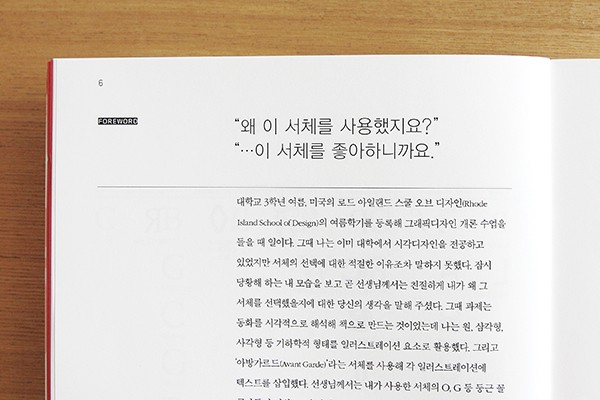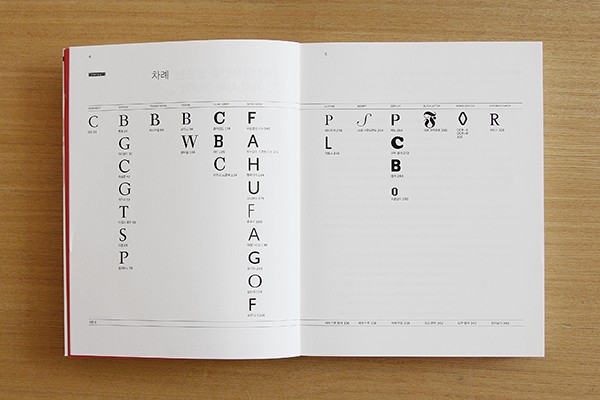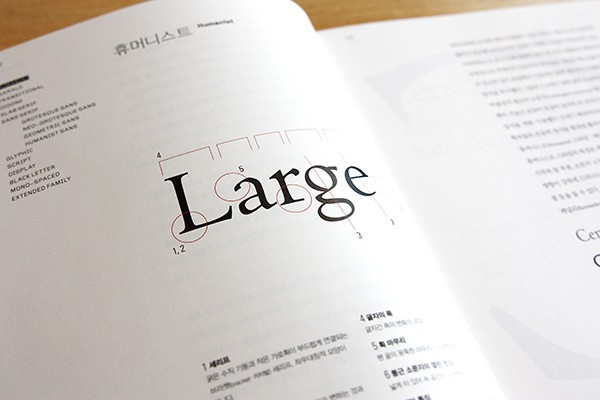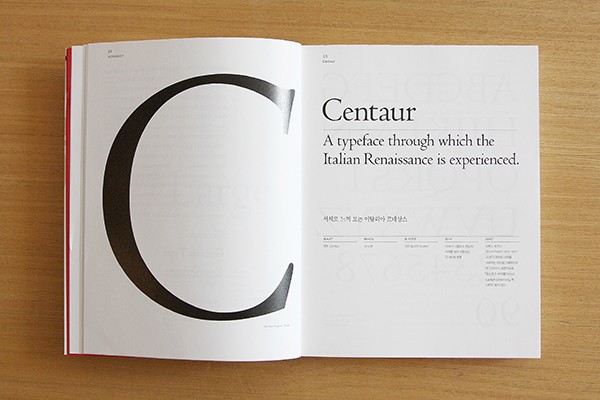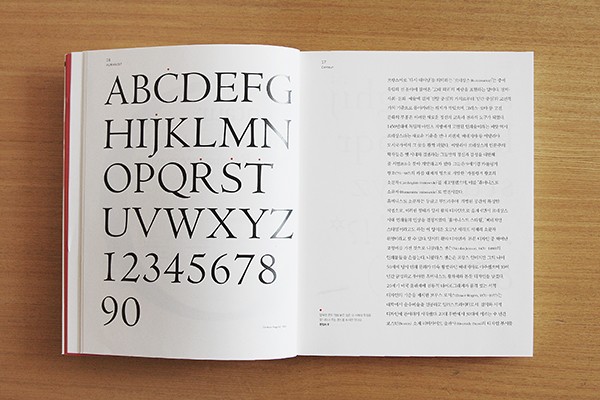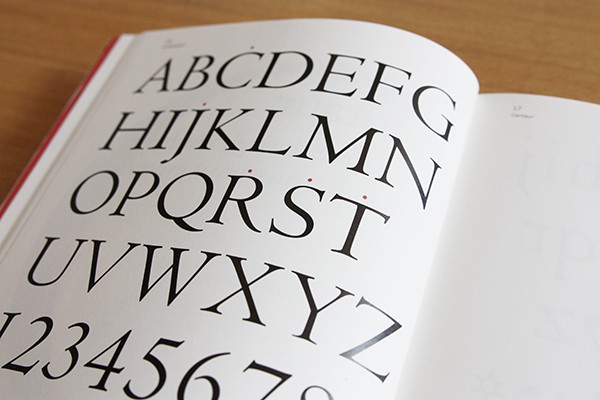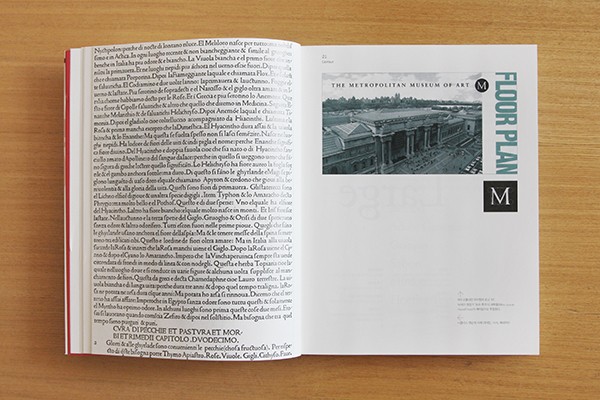
<좋은 디자인을 만드는 33가지 서체 이야기> : 기능과 아름다움이 검증된 서체 모음집
서체를 둘러싼 다양한 정보와 형태에 대한 이해는 모두 디자이너의 시각적 선택의 근거이자 문제 해결의 열쇠가 된다. 디자인을 하면서 콘셉트에 따른 이미지와 서체에 대한 고민을 해야 할 때가 많다. 전달에서 이미지에 따른 시각적인 부분도 크지만, 서체에 따라 디자인 성격이 달라지는 것을 볼 수 있다.
좋은 디자인을 만드는 33가지 서체 이야기
학생 때 이후로 다시 한 번 펼쳐 본 <좋은 디자인을 만드는 33가지 서체 이야기>는 디자인을 전공하는 학생이라면 분야를 가리지 않고 추천하고 싶다. ‘서체’는 디자이너가 갖추어야 할 기본 소양이라고 할 수 있는데, 흩어져있는 서체에 대한 정보를 타이포그래피 역사에서 기능과 아름다움이 검증된 서체들로 잘 엮어둔 고마운 책이다.
1. 센토 – 서체로 느껴 보는 이탈리아 르네상스
2. 벰보 – 황금의 파트너십이 창조한 서구 로만 서체의 원형
3. 게라몬드 – 우아하고 품격 있는 세리프 서체의 원형
4. 캐슬론 – 프랑스에는 게라몬드가, 영국에는 캐슬론이
5. 가우디 – 미국에서 탄생한 특별한 로만 서체
6. 타임스 로만 – 신문을 위해 탄생한 ‘전천후’ 서체
7. 사봉 – 타이포그래피의 거장 얀 치홀트가 남긴 선물
8. 팔라티노 – 펜글씨의 생동감이 특징인 로만 서체
9. 베스커빌 – 18세기에 등장한 모던한 인물의 모던한 서체
10. 보도니 – 이탈리아가 선사한 ‘서체의 꽃’
11. 발바움 – 가장 독창적인 독일의 낭만주의 서체
12. 클라렌든 – 산업혁명 시대에 나타난 본문용 서체
13. 시티 – IBM 로고의 모태가 된 서체
14. 센추리 스쿨북 – 두 세대에 걸친 재능과 땀이 만들어 낸 서체
15. 프랭클린 고딕 – 미국의 모더니즘을 보전하는 서체
16. 악치덴츠 그로테스크 – 신 타이포그래피의 전통을 잇는 서체
17. 헬베티카 – 20세기 공식 서체
18. 유니버스 – 타이포그래픽 컬러 팔레트
19. 퓨추라 – 바우하우스의 정신을 실현한 서체
20. 아방가르드 – 미국 잡지 디자인의 황금기에 태어난 서체
21. 길 산스 – 가장 영국적인 서체
22. 옵티마 – 세리프와 산세리프의 최적의 배합
23. 프루티커 – 파리 공항의 사인을 위해 만든 서체
24. 퍼피추아 – 조각가 에릭 길의 조각한 듯한 서체
25. 리토스 – 그리스 시대의 명각 글씨를 표현하는 서체
26. 스넬라운드핸드 – 기품있고 정감있는시각적 메시지, 손글씨 서체
27. 페뇨 – 포스터 아티스트 카상드르의 아르데코 서체
28. 쿠퍼 블랙 – 사랑하지 않을 수 없는 푹신한 세리프
29. 블록 – 20세기를 연 ‘포스터 양식’의 산세리프 서체
30. 오클랜드 – 디지털 시대의 도래를 보여 준 비트맵 서체
31. 페트 프락추르 – 국가와 이념의 표상이 된 서체 양식
32. OCR-A, OCR-B – 광학 문자 인식 기술(OCR)을 지원하는 서체
33. 로티스 – 독일의 거장 오틀 아이허가 남긴 하나의 서체
알파벳 폰트 위의 붉은 점은 각 서체의 특징을 잘 나타내 주는 폰트를 표시한 것이다. – 편집자 주
하나의 서체 이야기에는 그 서체를 만든 사람의 이야기와 그 서체의 고유한 특성이 시각전달 디자인에 잘 사용된 예를 보여준다.
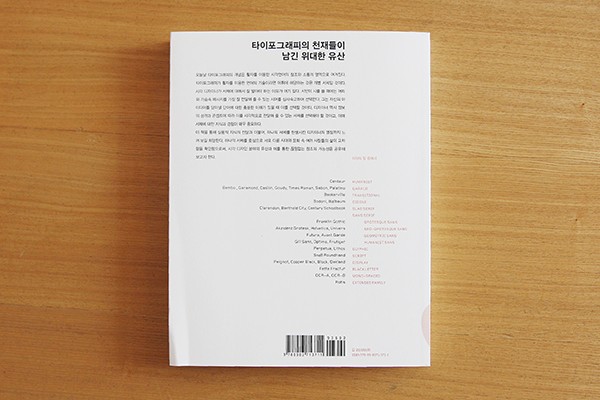
P. 8
오늘날 타이포그래피의 개념은 활자를 이용한 시각언어의 창조와 소통의 영역으로 여겨진다. 타이포그래피가 활자를 이용한 언어의 기술이라면 어휘에 해당하는 것은 개별 서체일 것이다. 시각 디자이너가 서체에 대해서 잘 알아야 하는 이유가 여기 있다. 시인이 시를 쓸 때에는 머리와 가슴속 메시지를 가장 잘 전달해 줄 수 있는 시어를 심사숙고하여 선택한다. 그는 자신의 아이디어를 담아낼 단어에 대한 충분한 이해가 있을 때 이를 선택할 것이다. 디자이너 역시 정보의 성격과 콘셉트에 따라 이를 시각적으로 전달해 줄 수 있는 서체를 선택해야 할 것이고, 이때 서체에 대한 지식과 경험이 매우 중요하다.
전달하고자 하는 내용에 의미 있고 적절한 서체를 이용하여 효과적으로 운용할 수 있는 능력은 디자이너들에게는 끊임없이 노력해야 할 부분이다. 디자인에 서체를 고르는 안목과 충분한 이해를 통해 사용했을 때 더 큰 효과로 다가올 것이다.